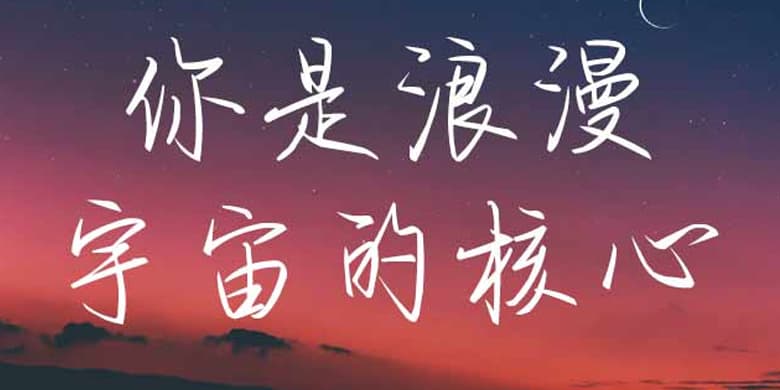
品牌:方正手迹设计师:刘殿儒发行时间:2020字库编码:简繁扩展(GBK)分类:常规书写·硬笔字体属性:精品字
该字体有着硬笔书法字的特点,笔触粗放苍劲不失潇洒,个性手写的灵动和英气体现得淋漓尽致,行如流水,从容不迫,结构严谨不呆板。适用于文艺类的书刊、品牌广告和产品包装设计,以及社交网络的个性化用字。